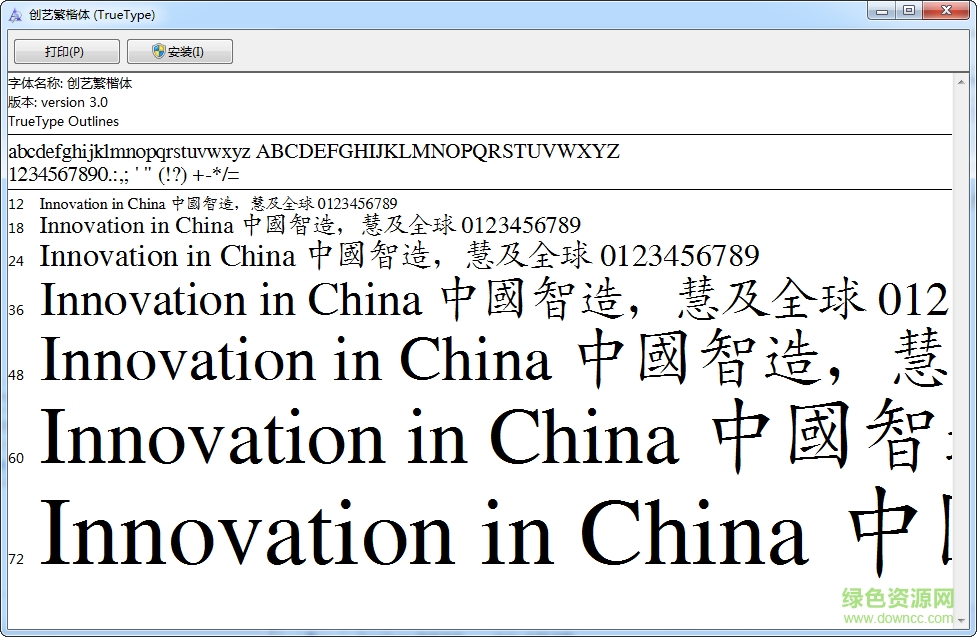
ctkaitisf是什么字體?ctkaitisf(創(chuàng)藝繁楷體)是一款結(jié)構(gòu)嚴(yán)謹(jǐn)?shù)?a href="http://m.lz0519.com/k/kaishuziti/" target="_blank">楷書字體,用筆工整又不失生動(dòng),其字體一般很少出現(xiàn)在書面文章中,只有在特殊的廣告或者雜志上才會(huì)有的見(jiàn),也非常適合用戶們進(jìn)行藝術(shù)字創(chuàng)作,需要的朋友快來(lái)綠色資源網(wǎng)下載這款繁體字體吧!
結(jié)構(gòu)方整:鋼筆楷書在結(jié)構(gòu)上強(qiáng)調(diào)筆畫和部首均衡分布、重心平穩(wěn)、比例適當(dāng)、字形端正、合乎規(guī)范。
講究用筆:鋼筆楷書的筆畫有提頓、藏露、方圓、快慢等用筆方法。
筆畫分明:鋼筆楷書的每一個(gè)筆畫的起筆和收筆都要交待清楚,工整規(guī)范,干凈利落,不能潦草、粘連。